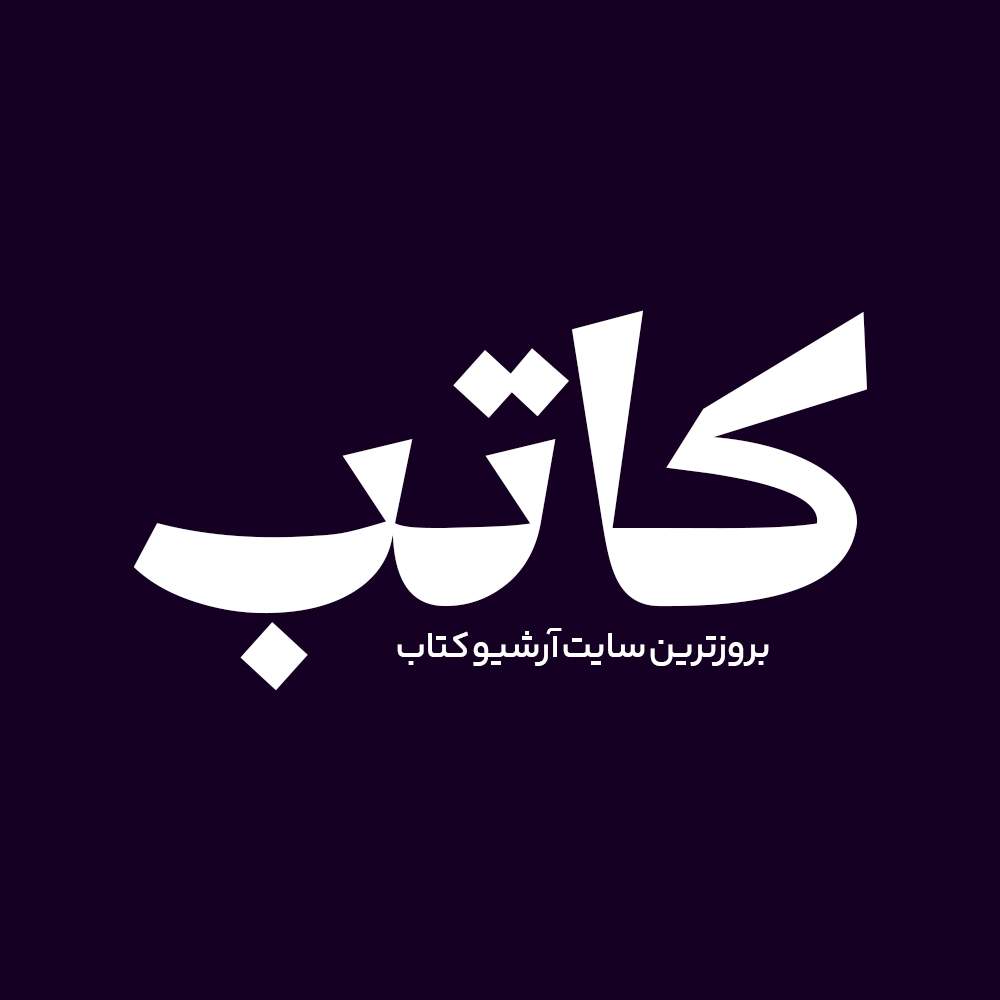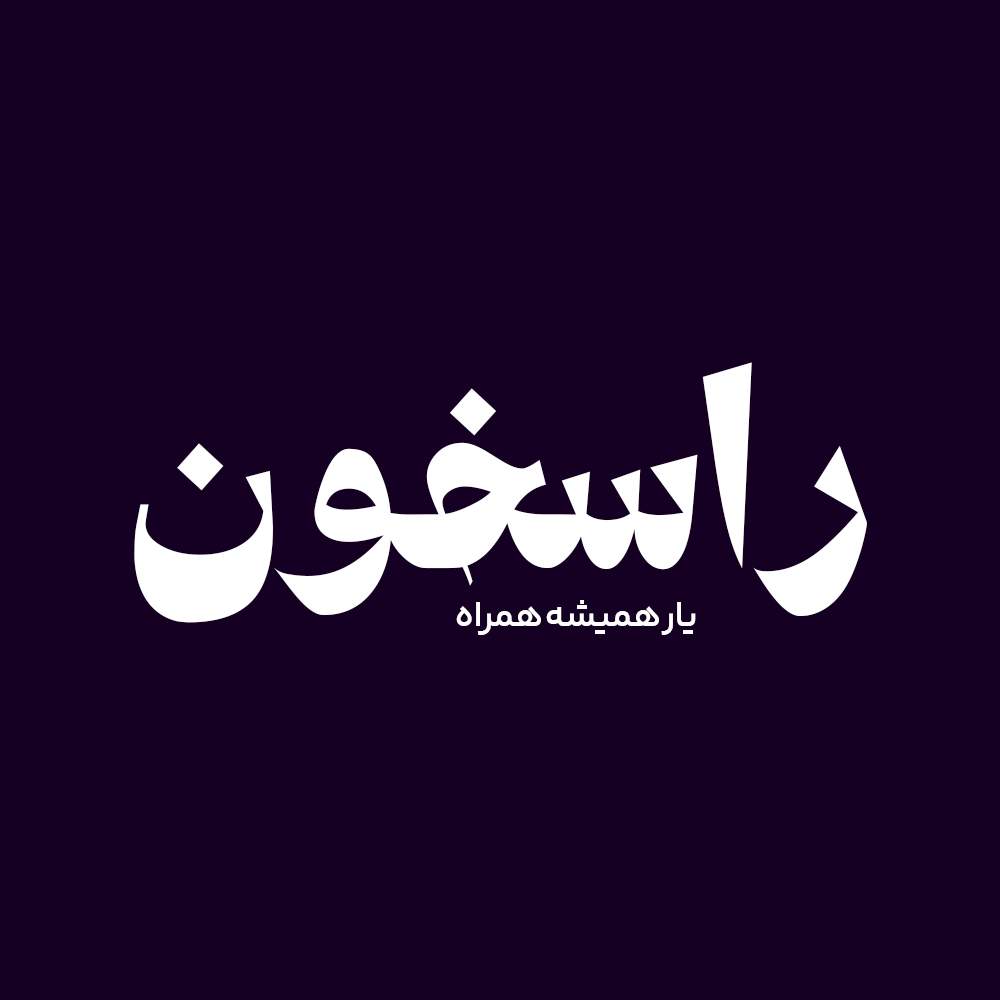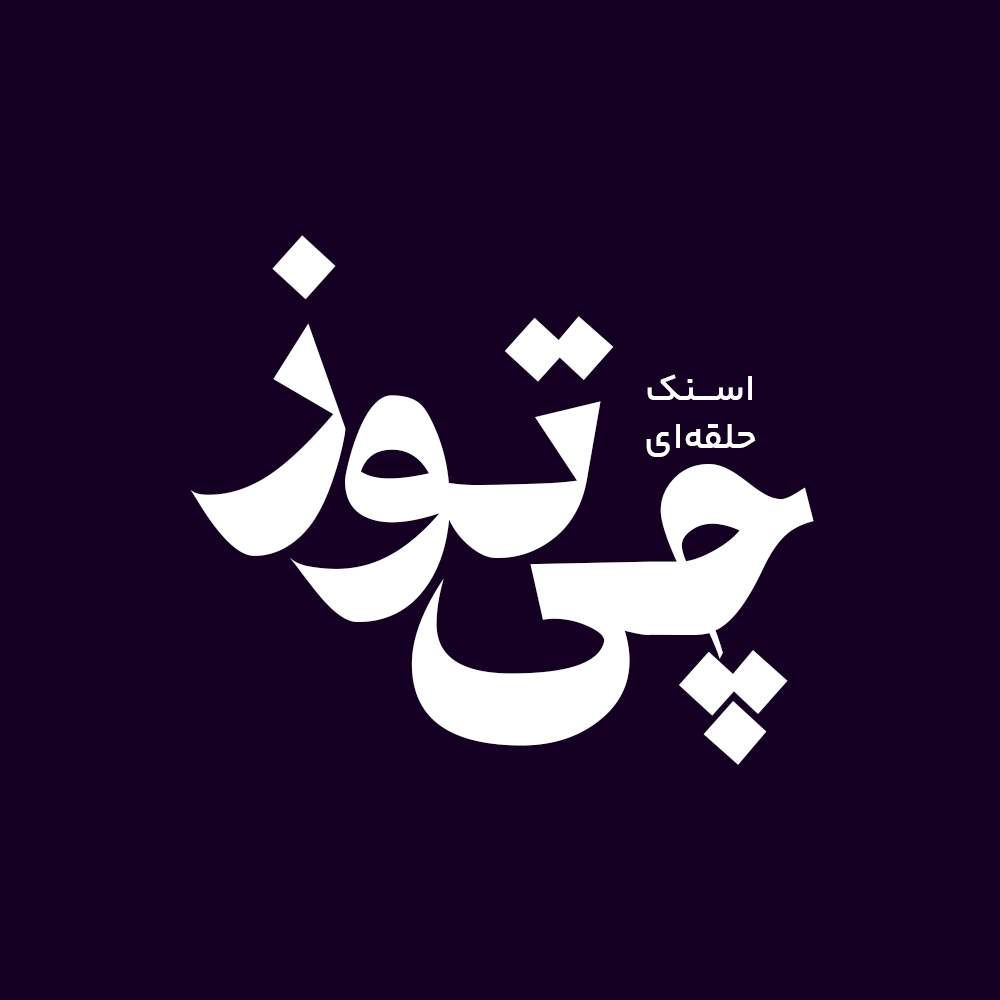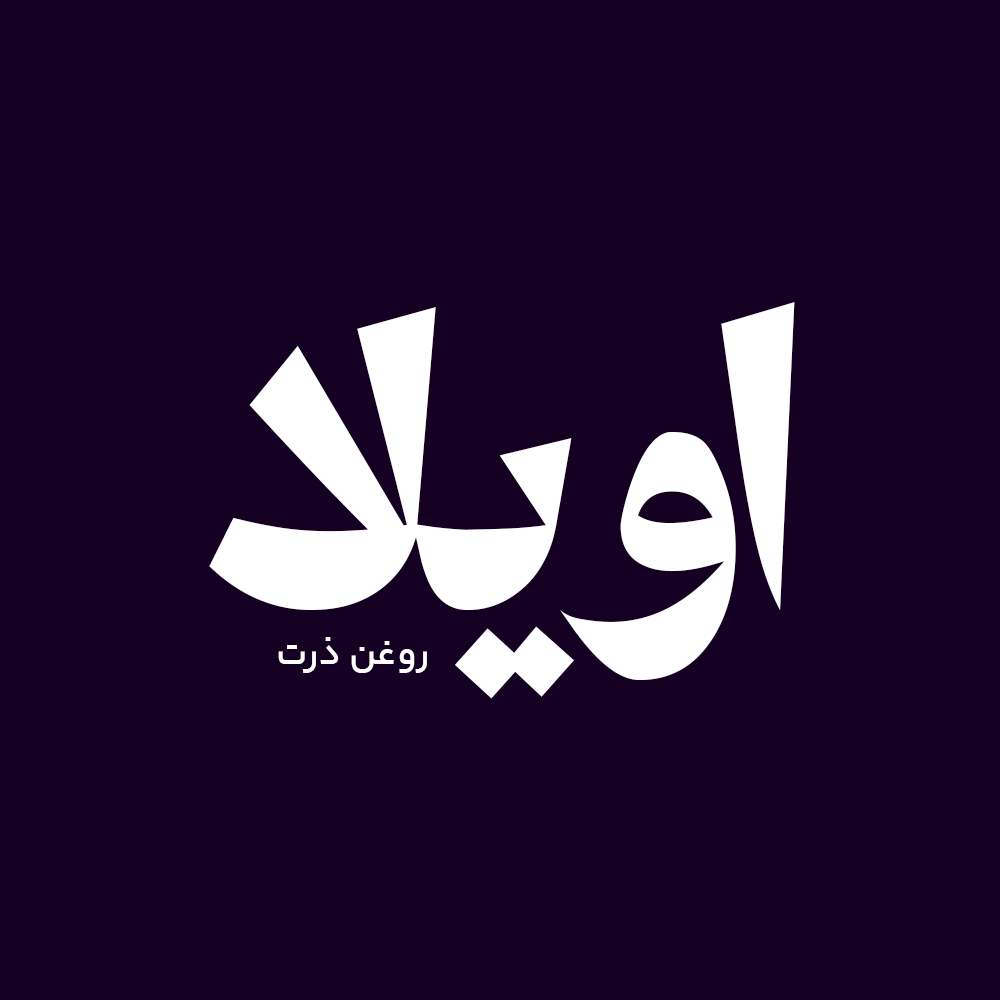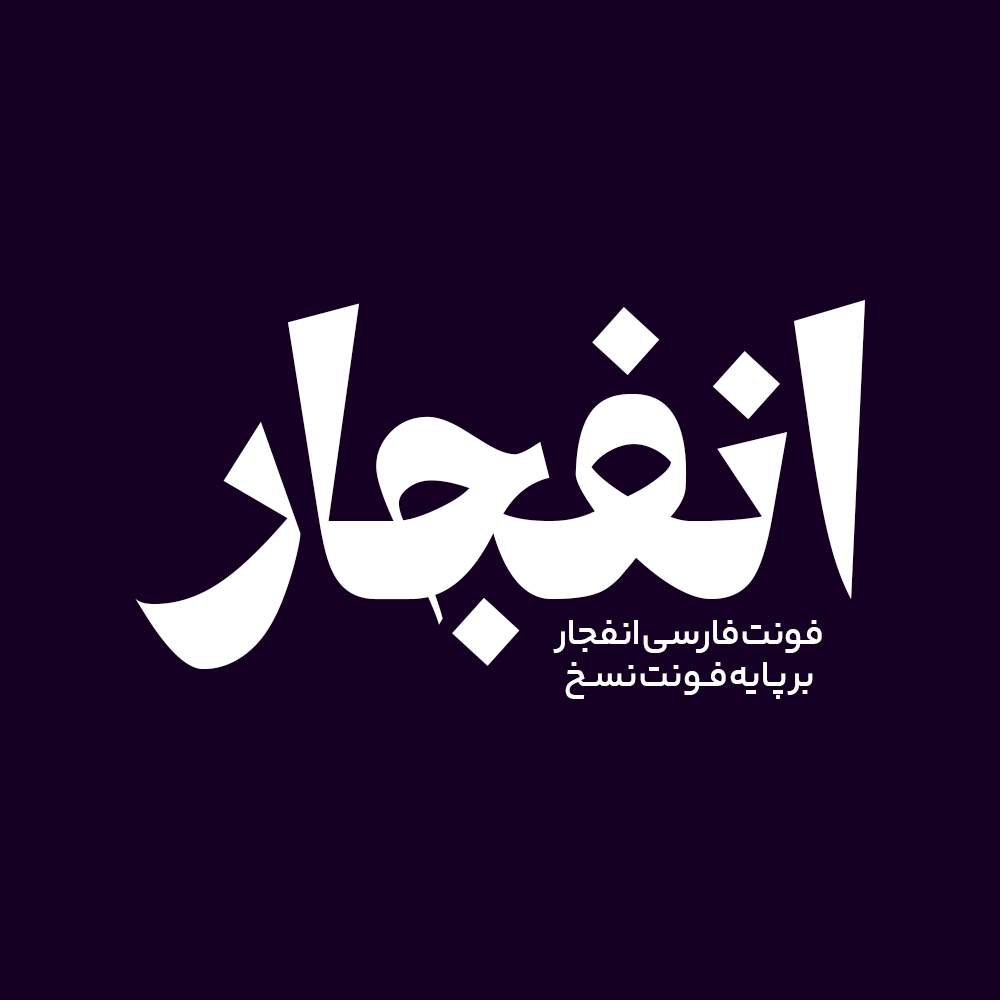
فونت فارسی انفجار Enfejar Font
فونت لوگوتایپ انفجار + نسخه جدید
فونت فارسی انفجار یک فونت بولد سبک نسخ و تک وزن با کاربرد طراحی لوگوتایپ و طراحی های مختلف همچون جلد کتاب و تولید محتوای متن های کوتاه و عناوین می باشد. این فونت با ساختار حروف خود مناسب استفاده در لوگوهای نوشتاری می باشد. همچنین از این فونت در طراحی تابلوهای چلنیوم هم به دلیل ساختار منحصر به فردش می توانید استفاده کنید. در ادامه برای شما نمونه تایپ های این محصول حرفه ای رو آماده کردیم که میتونید مشاهده کنید.
در فرایند بازطراحی فونت انفجار چه کارهایی انجام شد؟
- رفع باگ های گزارش شده توسط کاربران
- بازبینی و تنظیم فاصله گذاری بین حروف
- و…
کاربرد فونت فارسی انفجار
پیشنمایش و نمونه تایپ های فونت انفجار